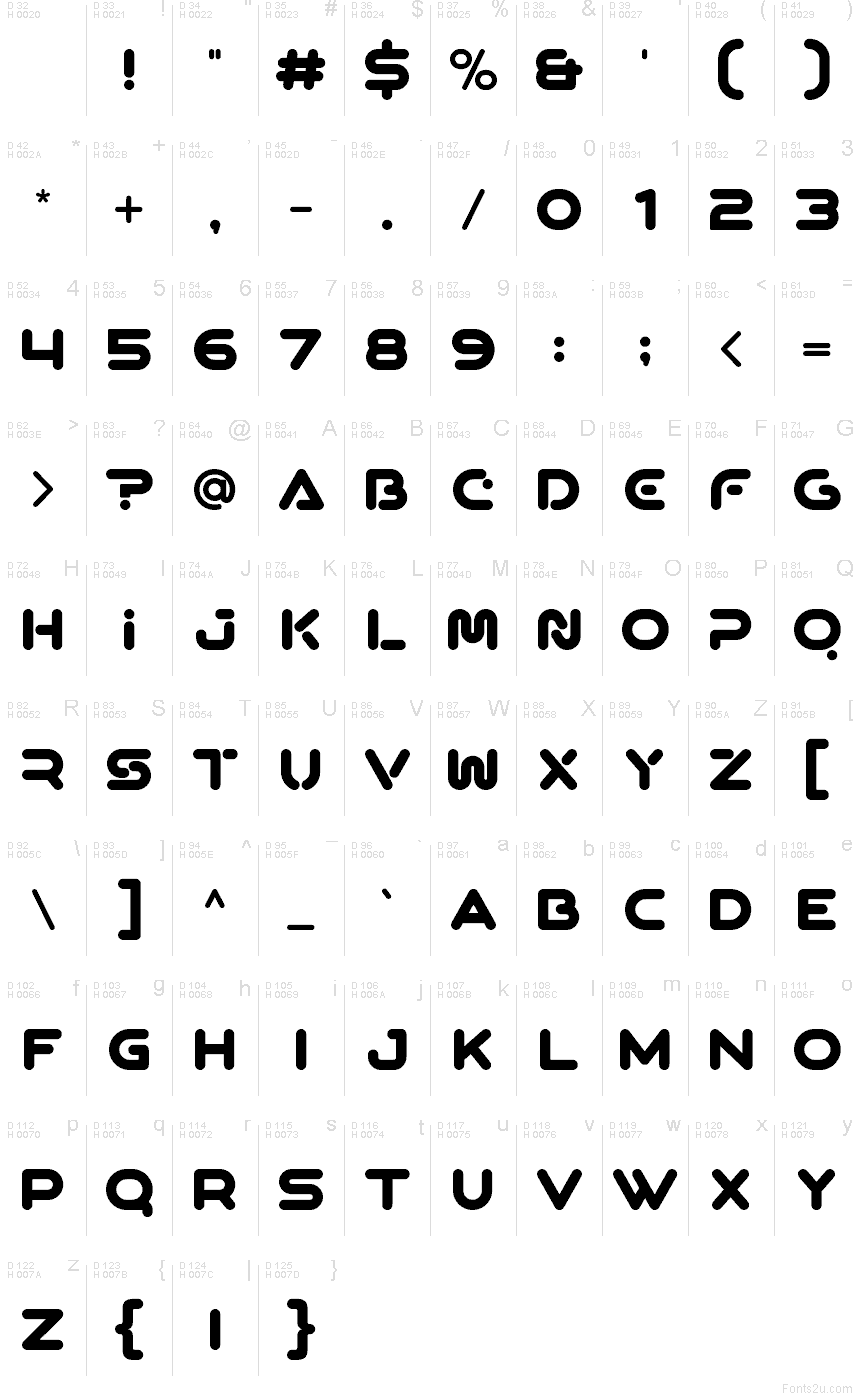
Saygen, da Ermedia Studio, é uma fonte display futurista e gratuita, com traços grossos e arredondados e letras geométricas largas. As curvas dobram-se para dentro em ganchos compactos, e aberturas em várias formas conferem ao letreiro um visual segmentado e mecânico.
Como destaque gráfico para embalagens de música eletrônica, o design lembra os botões arredondados e os circuitos sinuosos dos sintetizadores físicos. Essas mesmas características se adaptam perfeitamente a cartazes de fliperama e à identidade visual de eventos de tecnologia. Seu melhor uso são as embalagens musicais, onde as curvas encorpadas fazem com que o letreiro quase pareça uma peça de equipamento.